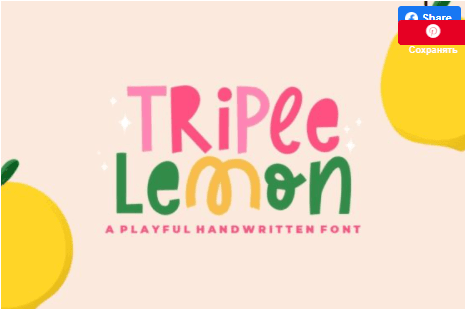
Triple Lemon Font
Triple Lemon — забавный и очаровательный шрифт для дисплея. Его можно использовать для создания красивой надписи на футболках, детских книгах, брендинге, малом бизнесе, обложках книг, канцелярских товарах, маркетинге, блогах, журналах и многом другом. Этот шрифт имеет кодировку PUA, что означает, что вы можете легко получить доступ ко всем глифам и росчеркам!